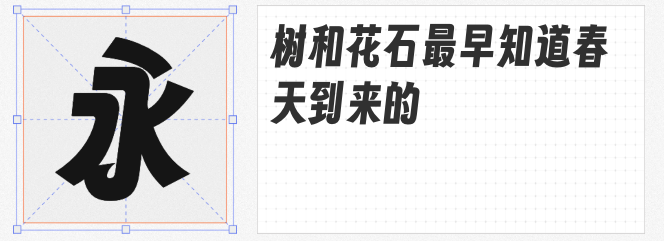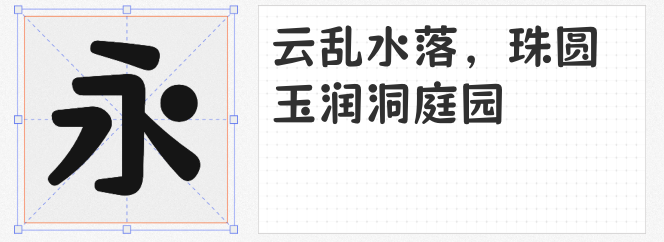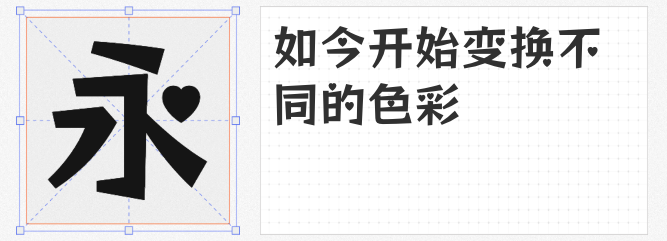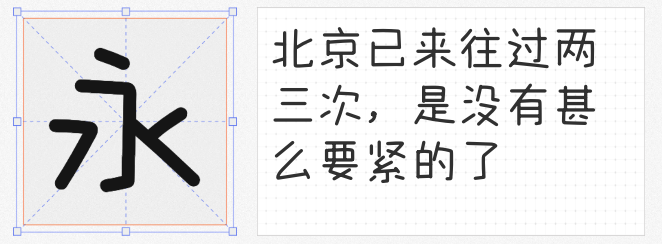
在设计领域,可爱风格的字体总能凭借其独特的魅力,为作品增添天真烂漫的气息。今天就为大家推荐四款免费商用的可爱风字体,让你的设计轻松“萌”出圈。
字魂扁桃体在得意黑的基础上大胆创新,加粗字重、略微加宽字身,让整体重量感显著提升。其标志性的喇叭口设计更是点睛之笔,使得意黑原本的微笑弧度“卷”出了新花样,充满了无限活力与个性。汉字结构的丰富性为喇叭口小卷带来了无限可能,无论是用于海报标题还是创意包装,都能瞬间吸引目光。
大宝桃桃体 Regular专为大宝知识星球打造,它将圆点部件巧妙地换成爱心,瞬间让整个字体可爱度爆棚。这款字体十分契合儿童、母婴产品以及萌系动画等场合,能为其增添天真可爱、无拘无束的活力。无论是作为标题还是正文字体,都能营造出萌萌的氛围,让人看了心生欢喜。
猫啃珠圆体源于标小智龙珠体,在保留其动感活泼俏皮可爱风格的基础上,将笔划调整为圆润风格,别有一番风味。它同样适用于儿童、母婴产品以及萌系动画等场景,能为设计注入满满的童趣。无论是用于品牌标志、宣传海报还是儿童读物的排版,都能展现出独特的魅力。
字帮玩酷体如其名,字形风趣,笔画多元,字形错落有致,风格轻松玩趣。它收录了GBK编码共20923个文字及987个符号,能满足各种使用场景的需求。无论是可爱风格的网页设计、游戏界面还是周边产品包装,字帮玩酷体都能轻松驾驭,为作品增添一份别样的趣味。
这四款免费商用的可爱风字体,各有特色,能为你的设计带来更多的创意和可能性。不妨在你的下一个项目中尝试使用它们,让设计焕发出不一样的可爱光彩!